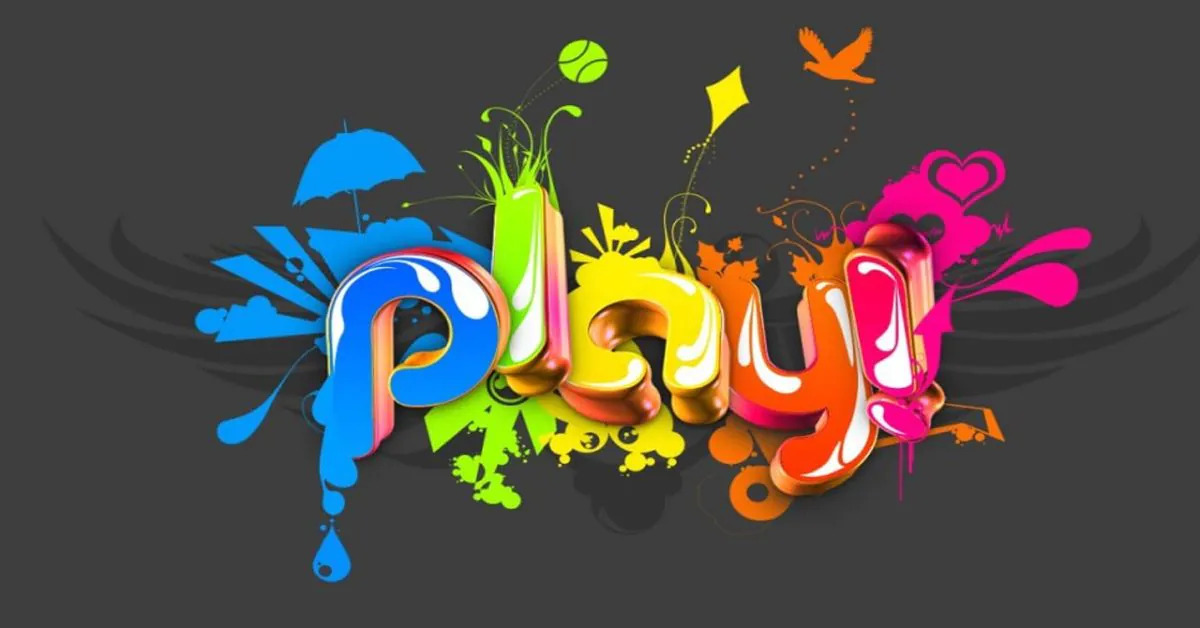
Font chữ 3d là gì và hiệu ứng nổi bật trong thiết kế bao bì?
Font chữ 3d là nhóm phông chữ được thiết kế để tạo ra ảo giác về không gian ba chiều thông qua các kỹ thuật đồ họa như đổ bóng, tạo khối và phối cảnh. Đặc trưng của dòng phông này là khả năng biến những ký tự phẳng thông thường trở nên sinh động, mang lại cảm giác chữ như đang nổi lên bề mặt vật liệu.
Sức hút của dòng phông này nằm ở tính trực quan sinh động. Các mẫu font chữ nổi 3d giúp thương hiệu dễ dàng nổi bật trong các không gian quảng cáo phức tạp, tạo ra ấn tượng mạnh mẽ về sự vững chãi và năng động.
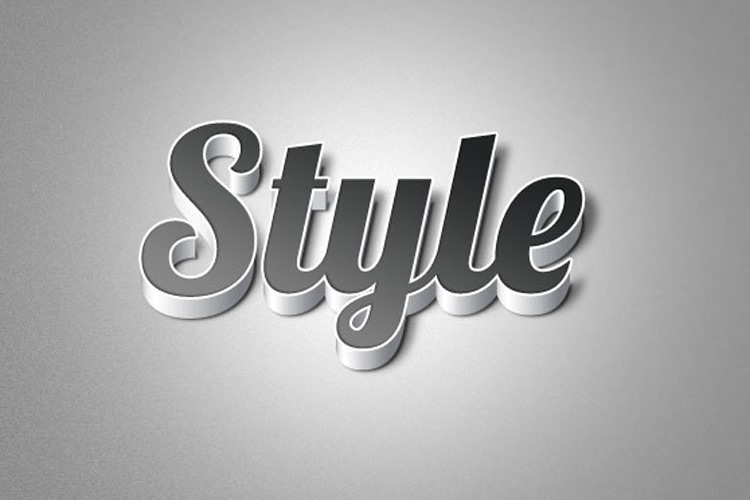
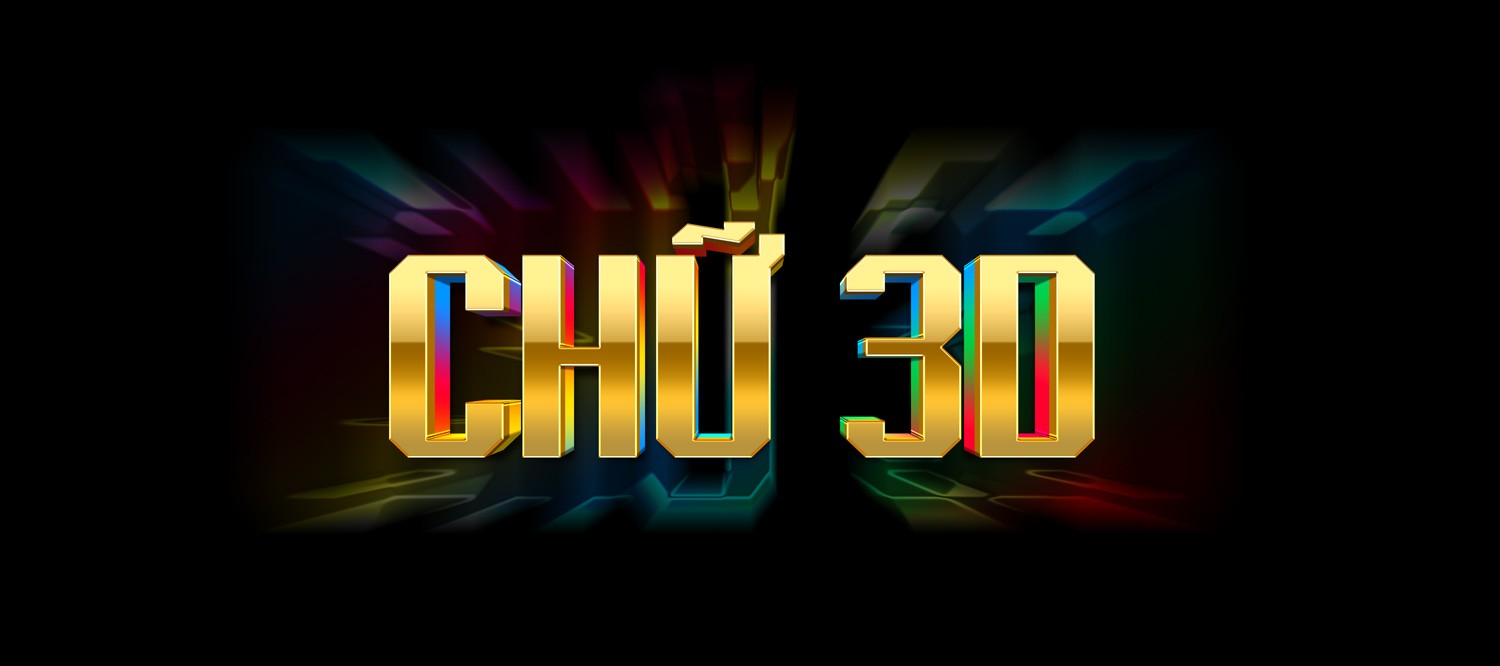
05 Ứng dụng tiêu biểu của kiểu chữ 3d đẹp trong sản xuất quảng cáo
Vẻ đẹp sinh động và khả năng tạo ấn tượng mạnh của phông chữ nổi giúp nâng tầm giá trị cho nhiều ấn phẩm truyền thông của đơn vị:
- Thiết kế bao bì hộp quà công nghệ cao: Sử dụng font chữ 3d cho tiêu đề trên các dòng vỏ hộp giấy đựng thiết bị điện tử hay phụ kiện thông minh. Hiệu ứng nổi khối tạo cảm giác sản phẩm hiện đại, cao cấp, giúp thương hiệu dễ dàng thu hút nhóm khách hàng yêu thích sự đổi mới.
- Sản xuất biểu trưng và kỷ niệm chương vinh danh: Kiểu chữ này cực kỳ lý tưởng để thiết kế nội dung khắc trên các khối pha lê hoặc gỗ. Độ sắc sảo của tệp thiết kế giúp máy khắc laser tạo ra những đường nét có độ sâu chân thực, tăng giá trị thẩm mỹ cho vật phẩm kỷ niệm.
- Gia công in UV trên các hiện vật tri ân: Logo lồng ghép cùng phông chữ 3d được in trên bình giữ nhiệt kim loại hoặc sổ tay da. Công nghệ in UV tại In Viva giúp các dải màu đổ bóng hiển thị sắc sảo, bền màu và tạo hiệu ứng chạm tay có độ nổi nhẹ độc đáo.
- Trang trí biển hiệu sảnh văn phòng: Sử dụng các mẫu font chữ 3d đẹp để làm chữ nổi mica hoặc inox dán tường. File vector chuẩn giúp thợ gia công cắt bế chính xác các góc cạnh, tạo không gian làm việc chuyên nghiệp và bắt mắt cho doanh nghiệp.
- Thiết kế poster sự kiện và banner ra mắt sản phẩm: Những dòng tiêu đề dùng phông chữ 3d rực rỡ dưới ánh đèn giúp chiến dịch truyền thông của đơn vị trở nên bùng nổ, dễ dàng ghi dấu ấn đậm nét trong tâm trí công chúng tham dự.
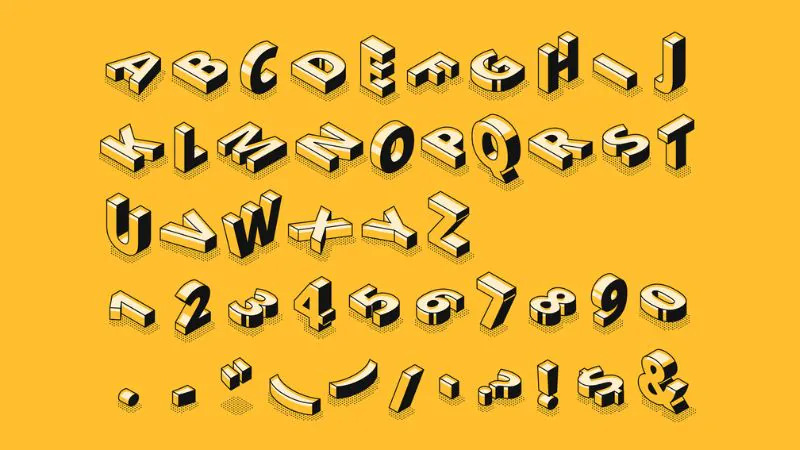
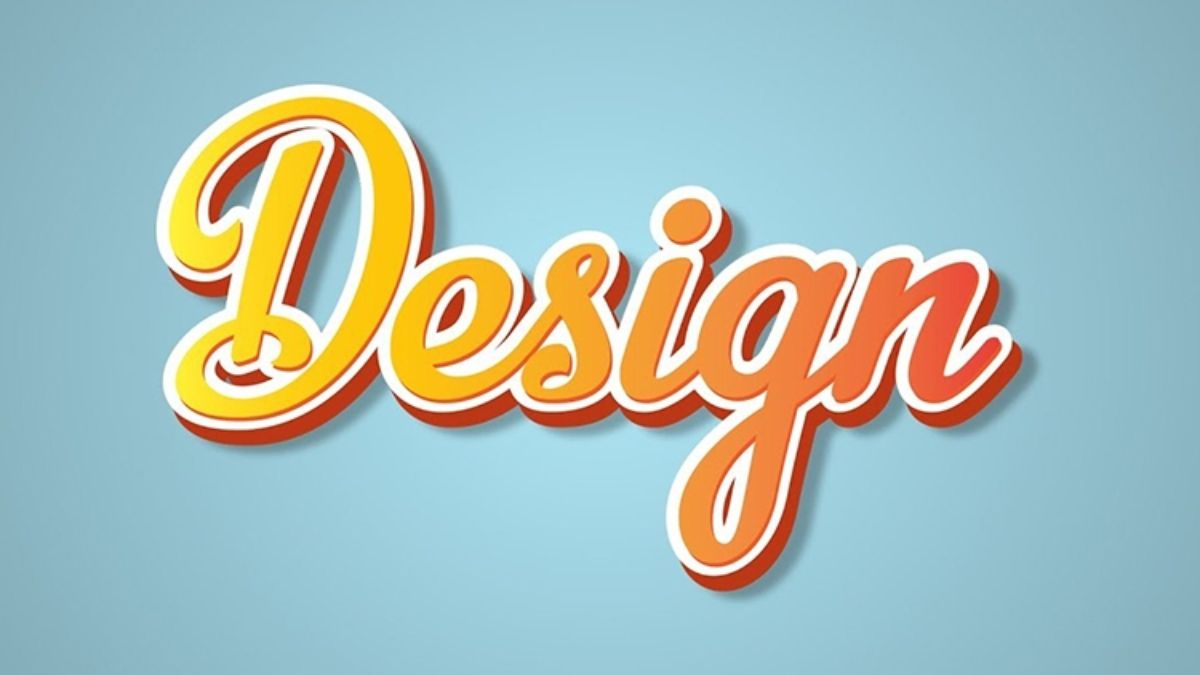
04 Tiêu chuẩn kỹ thuật khi xử lý font chữ nổi 3d phục vụ in ấn
Để hệ thống ký tự 3D hiển thị sống động và bền màu trên các thành phẩm thực tế như túi giấy cao cấp hay hiện vật lưu niệm, designer cần chú trọng:
- Kiểm soát dải màu Gradient: font chữ 3d sống động nhờ vào sự chuyển đổi màu sắc nhịp nhàng. Bạn nên thiết lập hệ màu CMYK chuẩn in ấn tại xưởng và yêu cầu mẫu thử để đảm bảo vùng sáng tối không bị phân lớp màu (banding) sau khi in.
- Tối ưu đường Path cho gia công bế nổi: Bước này đặc biệt quan trọng khi sản xuất nắp hộp quà dập nổi logo doanh nghiệp. Kỹ thuật viên cần làm mượt từng điểm neo trong file vector giúp khuôn bế thực hiện chính xác các cạnh khối, tạo hiệu ứng 3D rõ nét mà không làm rách giấy Ivory.
- Xử lý độ dày đường viền (Stroke) và bóng đổ: Khi in kích thước siêu nhỏ trên tem nhãn, các lớp bóng đổ của phông chữ 3d dễ bị mực làm bết dính. Designer nên giản lược bớt các lớp layer phức tạp hoặc tăng nhẹ độ tương phản màu sắc để đảm bảo chữ vẫn rõ ràng.
- Đảm bảo tính chính xác của phông chữ khi xuất file: Với các bộ phông 3D có cấu trúc phức tạp, bạn hãy luôn thực hiện lệnh “Expand Appearance” trong Illustrator trước khi bàn giao file cho xưởng in công nghiệp để loại bỏ rủi ro bị lỗi hiển thị trên các hệ máy khác nhau.